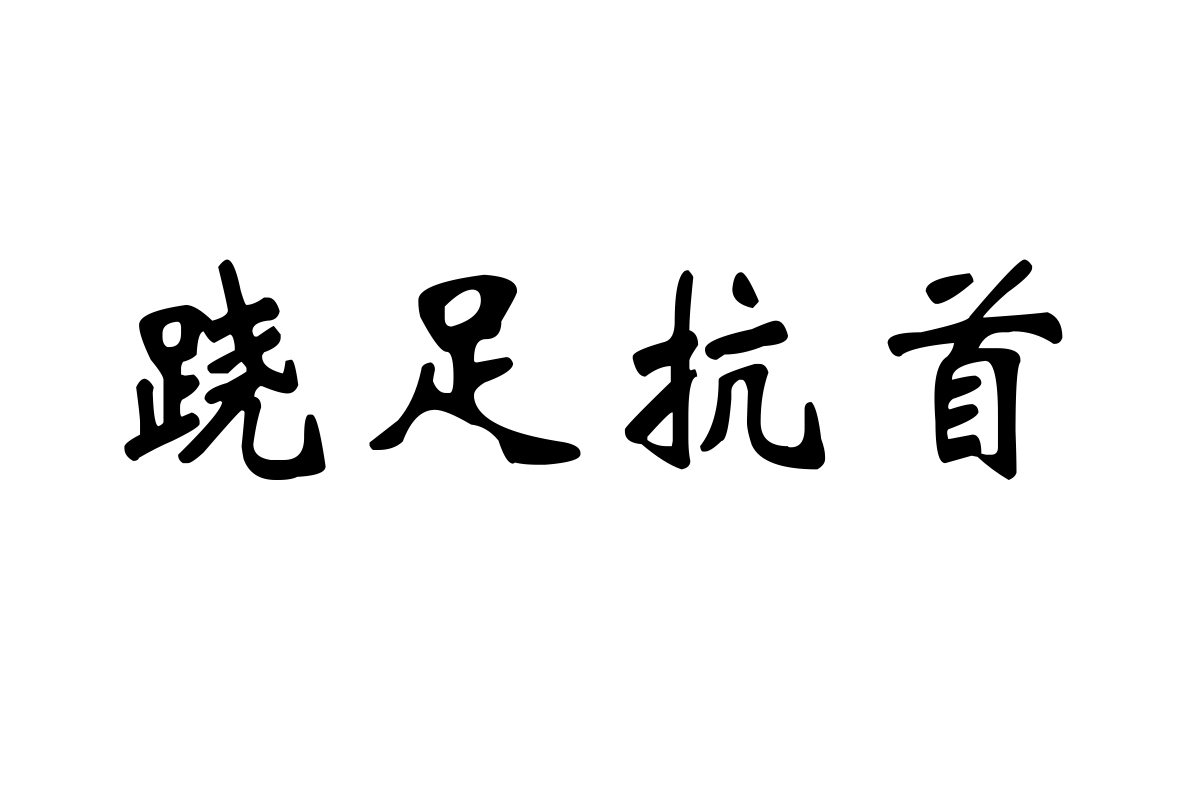
斑马新魏碑字体是一款具有现代感和艺术气息的书法字体,它结合了传统的魏碑书法风格和现代设计元素,创造出独特的视觉效果。这种字体适用于各种商业和艺术项目,包括广告、海报、网站设计等。
斑马新魏碑字体的特点如下:
1. 字形独特:这种字体的笔画流畅,结构紧凑,给人一种简洁而有力的感觉。它的字形类似于传统魏碑书法,但又带有一些现代元素,使得整体看起来更加时尚。
2. 线条清晰:斑马新魏碑字体的线条清晰,易于阅读。无论是大字还是小字,都能保持清晰的视觉效果,让人一目了然。
3. 适应性强:这种字体适用于各种场合,从正式的商业报告到创意的广告设计,都能展现出其独特的魅力。同时,由于其现代感的设计,也适合用于网络设计和社交媒体平台。
4. 可定制性强:斑马新魏碑字体支持多种字符集,包括中文、英文、数字等,可以根据需要定制不同的样式和效果。这使得它在实际应用中更具灵活性和多样性。
总之,斑马新魏碑字体是一款具有现代感和艺术气息的书法字体,适用于各种商业和艺术项目,能够为设计带来独特的视觉效果和表达力。